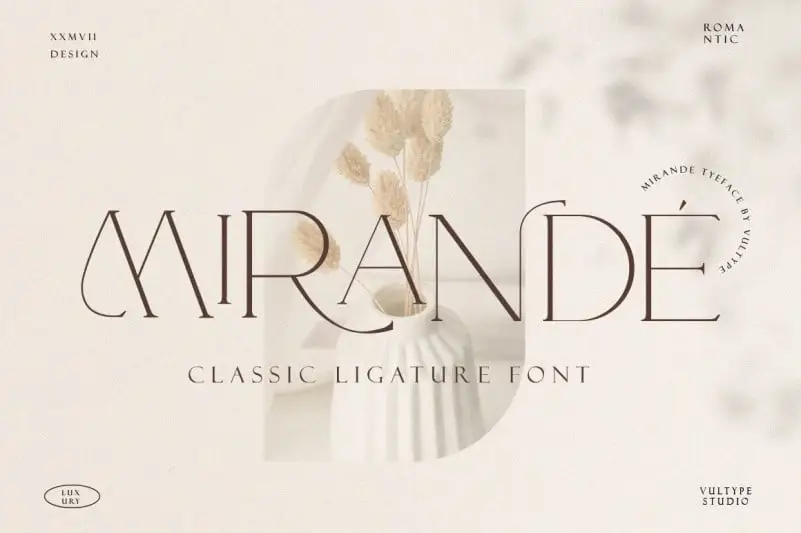
Mirande Serif Font é uma nova tipografia moderna que traz ambos os tipos maiúsculos e minúsculos complementados por alternativas idênticas feitas com carinho. Ela tem um contraste de estilo minimalista que está intimamente ligado à moda há décadas. Esta fonte se destaca tanto pela sua modernidade quanto pela nostalgia, sendo adequada para logotipos, mastheads e citações destacadas. Suas linhas são ideais para combinar com uma tipografia sans-serif minimal ou até mesmo um script leve. Sempre procurando oferecer recursos úteis para designers gráficos apaixonados, o Mirande Serif Font é perfeito para estilos que valorizam a simplicidade e paixão contemporânea em equilíbrio com memória nostálgica.